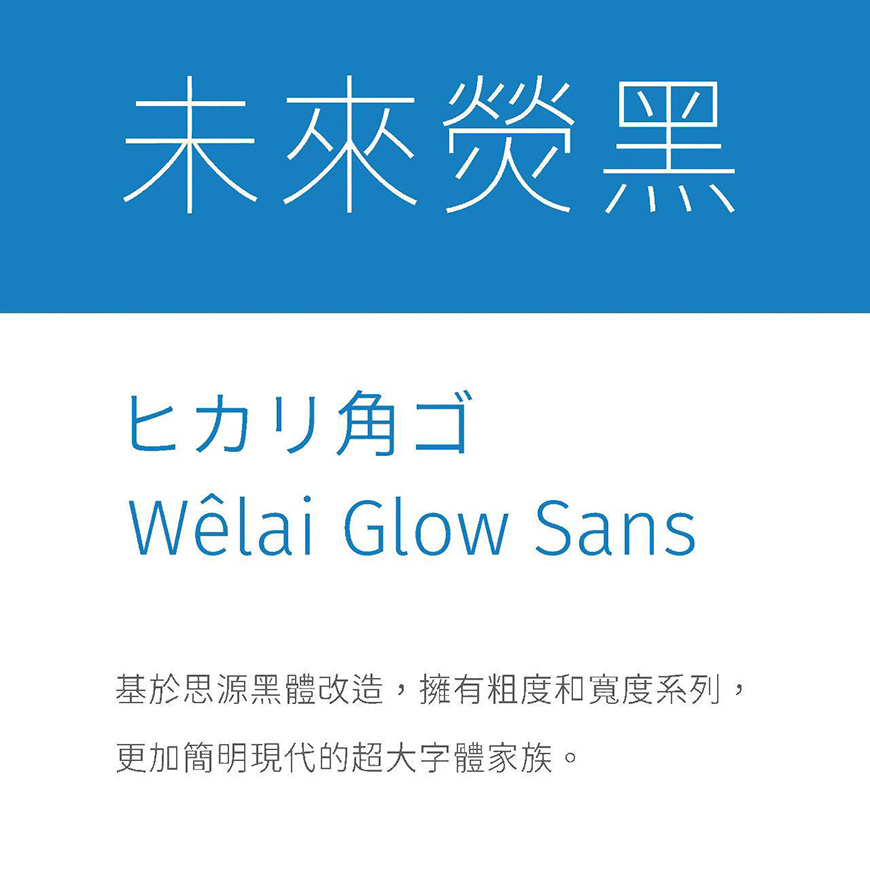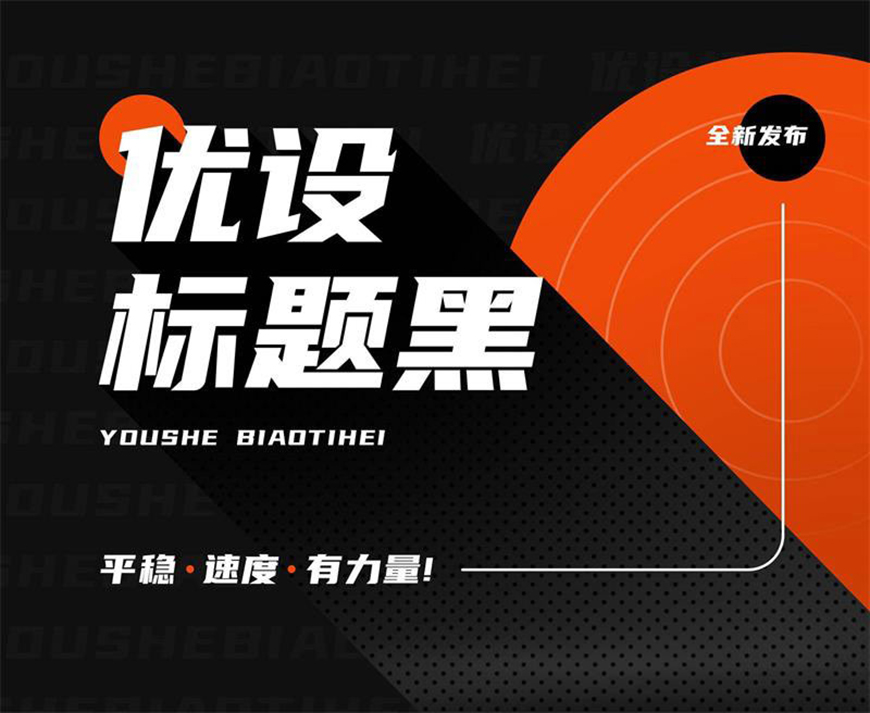
# 77款免费可商用字体大合集
# 黑体
# 思源黑体 (opens new window)
思源黑体属于无衬线黑体,支持繁体中文、简体中文、日文及韩文,并且各有 7 种字体粗细(ExtraLight、Light、Normal、Regular、Medium、Bold 和 Heavy)。完全支持繁体中文、简体中文、日文和韩文,还包括来自我们颇受欢迎的 Source Sans 字体家族的拉丁文、希腊文和西里尔文字形。
# OPPO Sans (opens new window)
字体采用全新骨架,中宫自然舒适,结构稳定,字形舒展,奉行简洁真实,把握更多细节,并针对移动端进行了像素级优化,长时间阅读也不会感到累。“简洁真实”是 OPPO 追诉的品牌美学,简化笔画,在提高屏幕显示的阅读体验的同时,也能够释放 OPPO 现代化科技美感。把握更多的细节处理,例如去除出脚,让 OPPO Sans 看起来更加简洁、干净。
# 阿里巴巴普惠体 (opens new window)
阿里巴巴惠普体属于无衬线黑体,共收录了 5 种字重(Light、Regular、Medium、Bold 和 Heavy),116,895 个全形汉字,西文字体 Alibaba Sans 共 7,205 个拉丁字母(2 种风格、共 11 种字重),覆盖 172 个语种(覆盖大部分欧语国家)。
# 阿里巴巴普惠体2.0 (opens new window)
5 月 14 日,在 2021 阿里巴巴设计周现场,阿里巴巴发布了 “ 阿里巴巴普惠体2.0 ” ,也是免费面向全社会开放下载和使用,并承诺在所有平台均可永久免费商用。目前阿里巴巴普惠体 2.0 共囊括 222841 个字符,覆盖全球 175 个语种。阿里巴巴普惠体 2.0 在原有基础上,优化了部分字体结构、新增了 4 个字重(字体粗细),还新增了泰文和越南文
阿里巴巴普惠体 2.0 版本共包含 9 款字重,其在原有的 5 款字重基础上,新增了 45 Light、65 Medium、85 Bold、105 Heavy 等 4 款字重。本次升级进一步完善了普惠体家族的字重体系,使得排版场景更加丰富和多元。
在优化字体结构方面,调整了“勺”部件相关字体,撇与点的间距、调整了“钅”部件相关字体,左右部件的间距。同时调整了部分笔画的衔接处,处理的更整体。
阿里巴巴普惠体 2.0 还新增了泰文和越南文。
# 优设标题黑 (opens new window)
「优设标题黑」是优设与字由在 2019 年底联合发布的优设首款免费可商用中文字体 (opens new window),是一款适用于标题的倾斜黑体。这款字体的设计初衷是为了帮助设计师们减少在这类型标题字设计上耗费的时间和精力,也为了给读者更好的阅读体验。这是一款兼具速度与力量感的倾斜黑体标题字体,整体字形粗壮沉稳,非常适用于各类品牌广告和产品包装设计的标题上。这款字体包括 6763 个汉字和字符,支持简体中文。
# 霞鹜新晰黑 (opens new window)
「霞鹜新晰黑」是一款衍生于 IPAex ゴシック的简体中文黑体字型。这是一款基于 IPAex 黑体的中文开源字体,是将日本写法的字体改造成简体中文写法的尝试。本字体尝试在 IPAex 黑体和霞鹜晰黑原有字形的基础上,将其改造成中国大陆的标准字形,更加适合中国大陆用户的需求。
# 仓耳与墨 (opens new window)
本字体基于中华人民共和国 GB2312-80 字符集汉字部分标准,TrueType 格式,共收容汉字 6763 个,英文及标点等常用字符 245 个。「仓耳与墨」含有五个字重,随着笔画粗细的变化,字体笔画的组合和形态都有所改变,整体形态也各不相同,可以互相搭配,应用范围较广。
# 江城正义体 (opens new window)
该字体含中文简体及英文字符共 6763 个,含繁体字符 6865 个。含有五个字重,字重的不同改变给字体带来了不同的视觉效果,同时也扩大了字体的适用范围。该字体在改造过程中将思源黑体的横向笔画进行减细处理,纵向笔画进行增粗处理,得到类似粗宋风格字体,削减横笔的粗细,使字体看上去更具现代感。
# 卓健橄榄简体 (opens new window)
该套字体含有共计 7050 个中文汉字,52 个英文字母,139 个阿拉伯数字及常用标点符号。「卓健橄榄简体」整体接近方形,长宽比例约为 1:1,使得字体在视觉效果上方正稳重,大小相同且方正规范的字形让字体更利于排版。该字体在设计的构思上细致精巧、别出心裁,将重心上移,使得字体更具时尚感。
# 975朦胧黑体 (opens new window)
975 朦胧黑体是作者@落霞孤鹜基于思源黑体边角朦胧化处理的一款免费商用字体。这款字体是在 975 黑体的基础上,内外边角加上圆角效果,使其有一种朦胧感。该字体含中文简体及英文字符共 6763 个,含繁体字符 4808 个。
# 江城尖刃黑 (opens new window)
该字体含中文简体及英文字符共 6762 个,含繁体字符 4807 个。江城尖刃黑最大的特点是在狮尾福腿黑体 SC 的基础上将突刺三角放大,使其更加尖锐显眼,这一特点使得字体有着更强的视觉表现力,展现出尖锐感、锋利感,也使得字体具有更好的辨识度。
# 站酷文艺体 (opens new window)
「站酷文艺体」设计新颖,尤其在笔画的处理上别出心裁,通过字形、细节的变化让整体视觉呈现简洁有力、清新淡雅的效果。笔画减少或去掉了弧度,相应进行直角或者圆角的变化处理,使字体几何感增强,突出了简洁的字体有力的字体特点。
# 站酷酷黑体 (opens new window)
「站酷酷黑体」的笔画极富设计感,整体气质独特,稳重又不失活力。在细节的处理上,该字体在笔画首尾端加入小三角,在保证识别度的前提下提高字体辨识度,使字体个性鲜明,结构独特。
# 站酷高端黑 (opens new window)
「站酷高端黑」由站酷网“汉字百人舞计划”出品,全部字形以众包的形式由分散在全国的 79 名设计师分别完成。笔画简洁、明朗、果断、有力,笔势节奏鲜明而富有气势。该字体的笔画横线右端均保持了同一形式、同一角度数的倾斜设计使字体个性鲜明,结构独特。
# 思源真黑体 (opens new window)
「思源真黑体」是基于思源黑体由 Adobe 和 Google 共同开发的一种字体,于 2014 年 7 月发布。思源真黑体在保留了思源黑体的优雅以及高可读性特色的同时,也在思源黑体的基础上对细节上做出了很多的调整与变化,使得整套字体看起来更加锐利清晰,更适用于大量文字阅读显示、代码编程、排版 (opens new window)、打印等。
# 未来荧黑 (opens new window)
未来荧黑是一个基于思源黑体、Fira Sans 和 Raleway 的开源字体项目,支持简体中文、繁体中文与日文。相比于思源黑体,未来荧黑的造型更加简明现代,版面效果清新轻快。未来荧黑的中宫与字面更加收敛,重心在字重之间经过了重新配置;笔画细节上处理得更加干练,简洁而平直化。
# 宋体
# 思源宋体 (opens new window)
思源宋体属于衬线字体,支持简体中文、繁体中文、日语和朝鲜语,拥有 7 种字重,且每一种都有 65,535 个字形,设计一致性将有助于获得更好的视觉美感。该字体还包含多个西方字形,支持拉丁语、希腊语和西里尔文脚本,这些字形均来源于 Source Serif。
# 字体圈欣意吉祥宋 (opens new window)
字体圈欣意吉祥宋是字体圈推出的第三款免费可商用字体,这是一套宋体风格的标题字,风格整体偏圆润古风,这套字涵盖国家 GB2312 编码标准的 6763 个中文字符,52 个英文字符,10 个阿拉伯数字,若干个标点符号,按需添加若干生僻字,共 7000 余字符。
# 一点明体 (opens new window)
「一点明体」的前身是刻石录明体,一点明体依照传承字形标准化文件《传承字形部件检校表》的推荐字形标准制作,力求遵从字理,展现传承汉字构字的科学系统。「一点明体」中的简体字部分传承旧字形,与我们平时常用的简体字字形上有较多差别。这一特点既不会影响阅读。又使得字体文艺复古气息大幅提升。